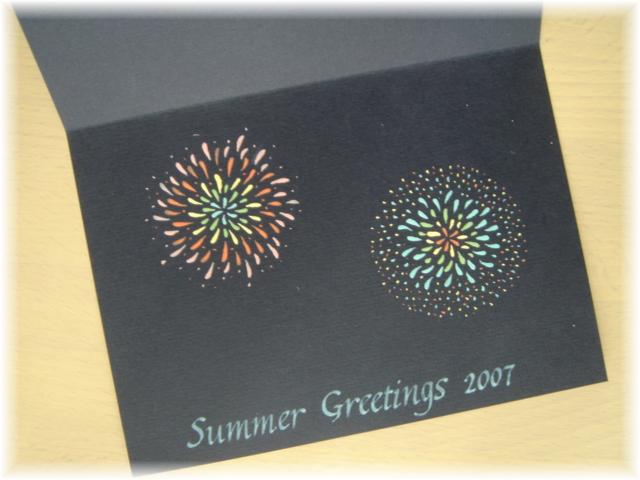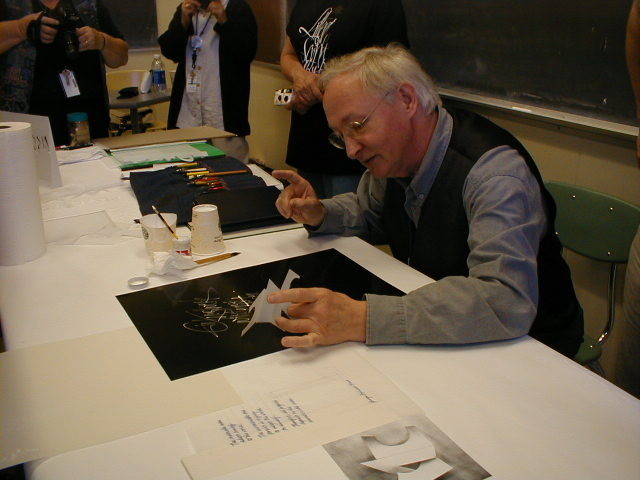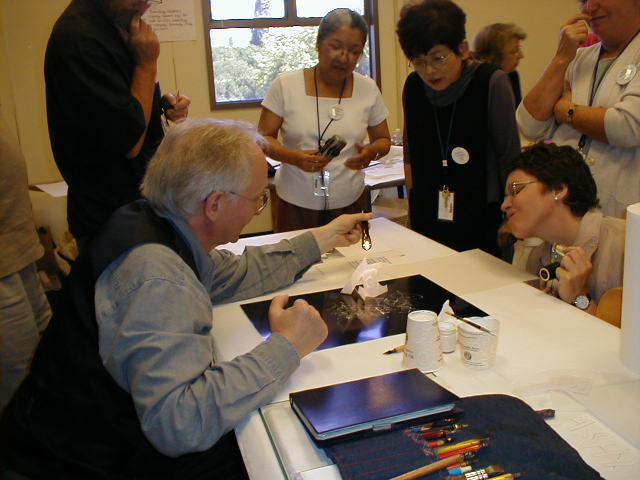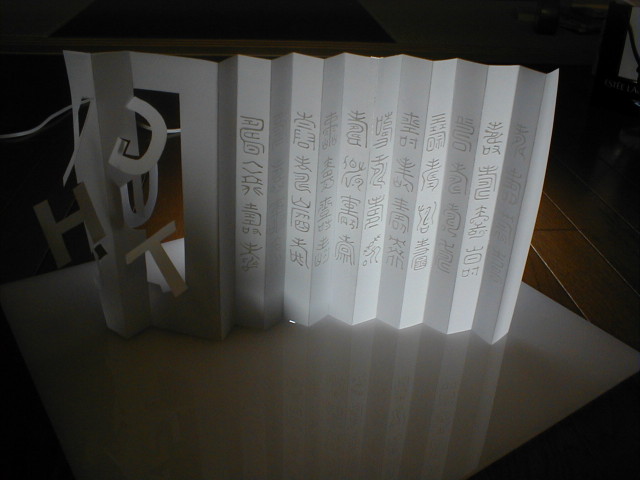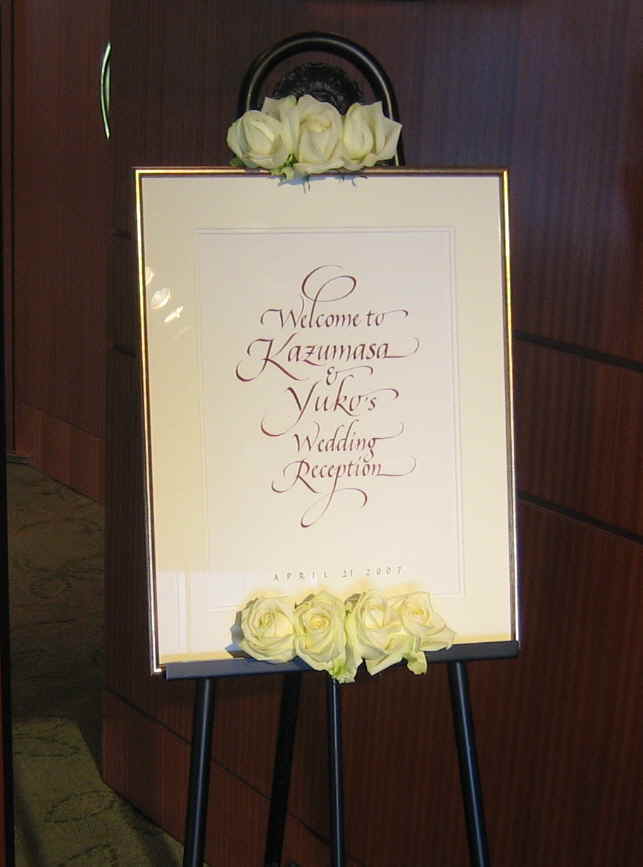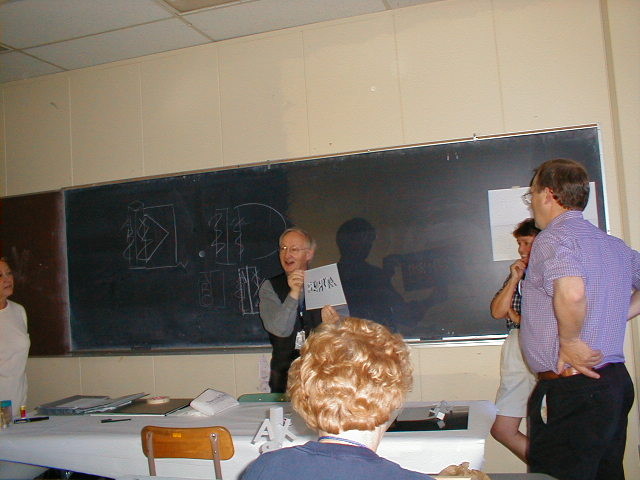
ヨーロッパでカリグラフィーロゴ
8月最後の日には、ヨーロッパで見つけた素敵な手書き文字をご紹介します。
とれも美しく素敵ですよ。
やはり手書きはいいよね〜。
どなたのデザインなのかわかりませんが、やはり手書きから作られる文字は素敵。本当に美しい。
やはりレストランやお菓子屋さんが、こういうイタリック体の流れるラインの文字の看板が多いですね。すべて入ってみたかったです。
う〜ん!可愛い・・・!
文字とニワトリがぴったり合ってます。
結局このお店には時間切れで入れず、アー残念。
もっともっと探せば見つかったことでしょう。手書きの美しいカリグラフィー文字を見つけた時の嬉しさ。
現在旅に出ているhさんもきっとたくさん写真を撮っていることでしょう。
また報告を楽しみにしていましょうね。
「虫たちの大合唱とフルオーケストラをBGMに青い月明かりの中、自然との共存とは?なんて考えながら地球さんに生かされている自分を感じています。そんな気持ちを表現していけたら」と、ここ銀河荘でインスピレーションを膨らませて、作品制作を目指していらっしゃるのだそうですよ。
熱いパッションin九州!
ここは九州、福岡にあるスタヂオ・ポンテさんのお教室。
先週の日、月に福岡へ
ワークショップを教えに行って参りましたスタヂオ・ポンテは、九州の地でカリグラフィー活動をしている初島さつきさんが主催しているカリグラフィーグループです。
ここポンテのスタヂオの床は国産杉の無垢板が張り詰めてあり、素足でとても気持ちがよいのです! 壁は和紙が貼ってあり、体に優しいスタジオなのです。
今回のワークショップはアクリル絵の具で下地を作ろうというもの。本来2日間のものを大急ぎの駆け足で1日にまとめて行ないました。
和紙の色付けでは、楮の和紙は全く問題ありませんが、濡れると弱くなる半紙にはみなさん悪戦苦闘。
でもこのぼろぼろさが芸術!何か訴えかけてきますですね。
これで何を作るのか、S嬢の腕のみせどころです。今後の創作を楽しみにしていましょう
九州の方たちの熱いパッションを感じさせる素晴らしいワークショップでした。おしゃべりも楽しく、出来上がりも見事です。今回のテクニックを使用してどんな作品がこれから出来上がるのか、本当に楽しみです。
おしあわせに
この春めでたく結婚されたかたから、インフォメーションのはがきをいただきました。
昨年末に以前クラスに来ていた方からの結婚が決まったという嬉しいメールから、4月の結婚式、そしてもう4ヶ月。しあわせなんだろうな〜。
自分でウエディングボードを書くというのは、カリグラフィーを生かす絶好のチャンス(☆゚∀゚) カリグラフィーから遠のいているとはいえ書きたいというご相談をいただき、それも嬉しいことでした〜。まあ、でも、結婚式は一大イベント!女性にとってはたいへんな準備です。今時の結婚式は、夢叶える素敵なもので、うらやましい〜(´▽`)
結局、忙しい彼女の代わりに、僭越ながら私が書きました〜.。゚+.(・∀・)゚+.゚
私が書くウエディングボードなどパターンがおよそ決まっているけれど、会場の雰囲気、基調の色、ドレスの画像を見せていただき、彼女のイメージをきいて、ドラフトをつくり、選択していただき作りました。
思い詰まった、思い出深い一枚、とても大きな画像なので、リサイズしたら鮮明じゃなくちょっと残念ですが、シンプルな花のデコレーションが素敵しょう〜。
どうぞ、末永くおしあわせに!
そんな私の夏の思い出を再現してくれたようなカードをいただきました。
昨日ご紹介したお菓子を送ってくださった、しろさんが、お手紙と一緒にカードもくださったのです。
濃紺の紙に、表側の星は一つ一つ手で貼ってあります。こんな小さな星型のパンチがあるのでしょうか。
2ミリくらい?かなり小さいです。星の大きさも何種類かあるし、紙も白いのやトレペなど変えてあります。
開くと中は鮮やかな花火。なんと!これ、手描きなのですね〜すごい…とってもきれいです。
絵の具は「クサカベ」のものだそうですよ!
この花火は「た〜まや〜」がぴったりの河原で見る昔ながらの花火ですね。浴衣と団扇が似合いそう。
一年前の記事とコメントをご覧になれば思い出してくださいますか〜?
さて、先週届いた宅急便。あら、お菓子?送り主はHさん。なぜに私に?
と包みをあけてみると、じゃ〜ん!これはこれは、「かまど」じゃないですか。
話題だった民芸調の包み紙です。興奮気味の私をもっと驚かせたのは同封のお手紙でした。
なんと送り主は、コメントでこのお菓子のパッケージのことを教えてくださった「しろさん」だったのです。
ただただ驚くばかりでした。
しろさん、ありがとうございます。あの時のことを覚えていてくださって、「かまど」を送ってくださるなんて!(私がどんな味?と聞いちゃったからでしょうか…ごめんなさ〜い)
はい、これが、そのシンプルな黒い箱です。
確かに包み紙からは想像できないモダンな箱ですね。(包み紙はよく見るとかわいい模様が描かれています。昔から伝わるお菓子の型図だそうですよ)
箱の上にのせたのが中身のお菓子です。昔々の塩を作るときの「かまど」を模した形なのだそうです。お味も美味。ひよこに似ているけれど、皮がいい風味でとってもおいしいです。白餡もしっとり。
「名物 かまど」と
黒一色の上に赤が効いています。
ホント、素敵な箱です。
これも何かを入れる箱に…と、棚のコレクションに加えている
mojitor-f でした。
クサカベ工場見学その3 絵の具作り
さてさて、昨日までは工場の生産過程を見て来ましたが、見学のあとはお楽しみの絵の具作り体験です。
まずチェさんの説明を聞きました。
「絵の具とは、何と何でできてるでしょう?」「はい、そうですね。顔料とメディウムです。では、どんな絵の具がありますか〜?」「油絵の具、水彩絵の具、アクリル絵の具、テンペラ、パステル、そしてアキーラ!」
優しく丁寧に教えて頂きました。透明水彩絵の具とガッシュ(不透明水彩絵の具)では、ガムアラビックの分量は異なるのだそうです。ガッシュの方がとても少ないので驚き。定着がよくないはずですね。
以前クラスのkumikoさんからサンプルを頂いてそのままになっているので、さっそく試してみなくちゃ
今日はウルトラマリンを作ります。昔は超高級なラピズラズリでしかできない色でしたが、今日では便利な合成ものがあります。顔料を各自頂き、水彩絵の具のメディウムであるガムアラビックで練って行きます。
とてもパレットナイフだけは無理なので、この練り練りの道具(モウラーとかなんとか言ったような・・・)で、さぁ練り練りの開始。
この日は東京ではこの夏の最高気温を記録した日で37度もあり、このお部屋もみんなの熱気で暑くなってきました。私も両手で頑張ります。
練った絵の具はツヤが出て、ねっとりいい感じです。最後まで練り上げたら、遂にチューブ入れです。
さっそくやってみます。mojitor-fさんの丁寧な手つき。
さて、入れ終えたらトントン空気を抜いてお尻を閉じます
そしてこれがお尻閉じ機(きっともっと素敵な正式名称があるはずですが)
私の作った絵の具は、なぜかチューブに印刷がなかったので、まるでムヒの様・・・・・。いえいえ、ムヒでもいいんです。自分で作った絵の具ですもの、感動もひとしお。
しかし、適当にガムアラビックを入れたので、一体メディウム何パーセントの絵の具なのでしょうね。ま、堅い事言わずに、水性絵の具としておきましょうね。
ゴッちゃん、得意そうですね・・・。本当にそうなんです。はい。
作りだされたアルファベットとそれに光を当てて出来上がった影と
その間に作り出される空間までがカリなんですなぁ・・・。
頭では理解していていも、設計図を作るのが大変です。
ゴッちゃん、楽しそうですね・・・。本当にそうなんです。はい。
二次元のカリと三次元のカリのコラボもありました。
黒い紙に光沢があるのも、その姿を映す役目もあるからです。
さて・・・ここからは、ほら、あれですよ・・・。夜中に一人で電気を消して
見てね・・・って・・・。
ちょっと、さむ〜い感じ・・・暑いですからね・・・欲しくないですか?
・・・ほら・・・っていうか・・・見えている姿はアルファベットなのに、
キャ〜、下で何かが蠢いている・・・?
あっちの世界の入り口ですかね・・・?やっぱり〜!?
ほら・・・背中なんて・・・スゥ〜って・・・。フフフ。
カリだってね・・・あっちに行くことあるんですよね・・・実は。
フフフ。
こんなことしてて・・・ぉお〜、もうすぐまずい時間ですね・・・。
私まで・・・スゥ〜って・・・。・・・えっ寝息ですか?